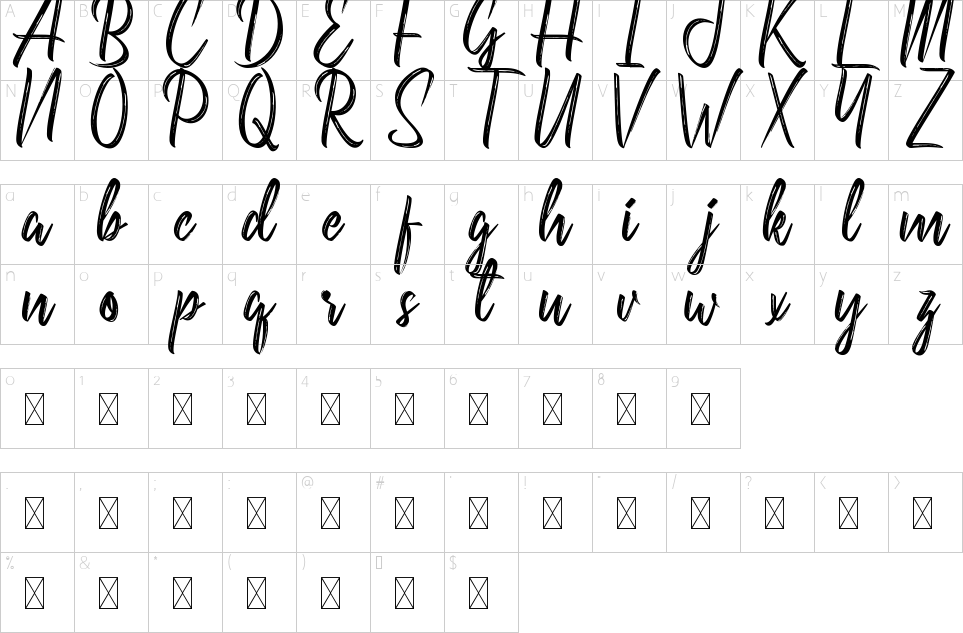
Disgracefull Font – Download Grátis
A Disgracefull Font é uma fonte que surgiu do trabalho árduo do designer desconhecido chamado raisproject. Esta fonte foi projetada para atender às necessidades de designers e criadores digitais buscando algo especial e único. Com seu design minimalista mas com arrojo, a Disgracefull Font é perfeita para criar textos com uma aparência versátil e moderna. Ela se destaca por sua simplicidade e força no layout de design gráfico, sem perder o charme da personalização que tanto os designers procuram em suas criações digitais. Desenvolvida sob demanda por criadores brasileiros ou internacionais, a Disgracefull Font foi baixada 2016 vezes desde sua publicação, evidenciando seu valor e popularidade entre o público de fontes gratuitas. Engajante, versátil e de fácil implementação, essa fonte pode ajudar você a destacar em seus projetos de design com um toque distinto.